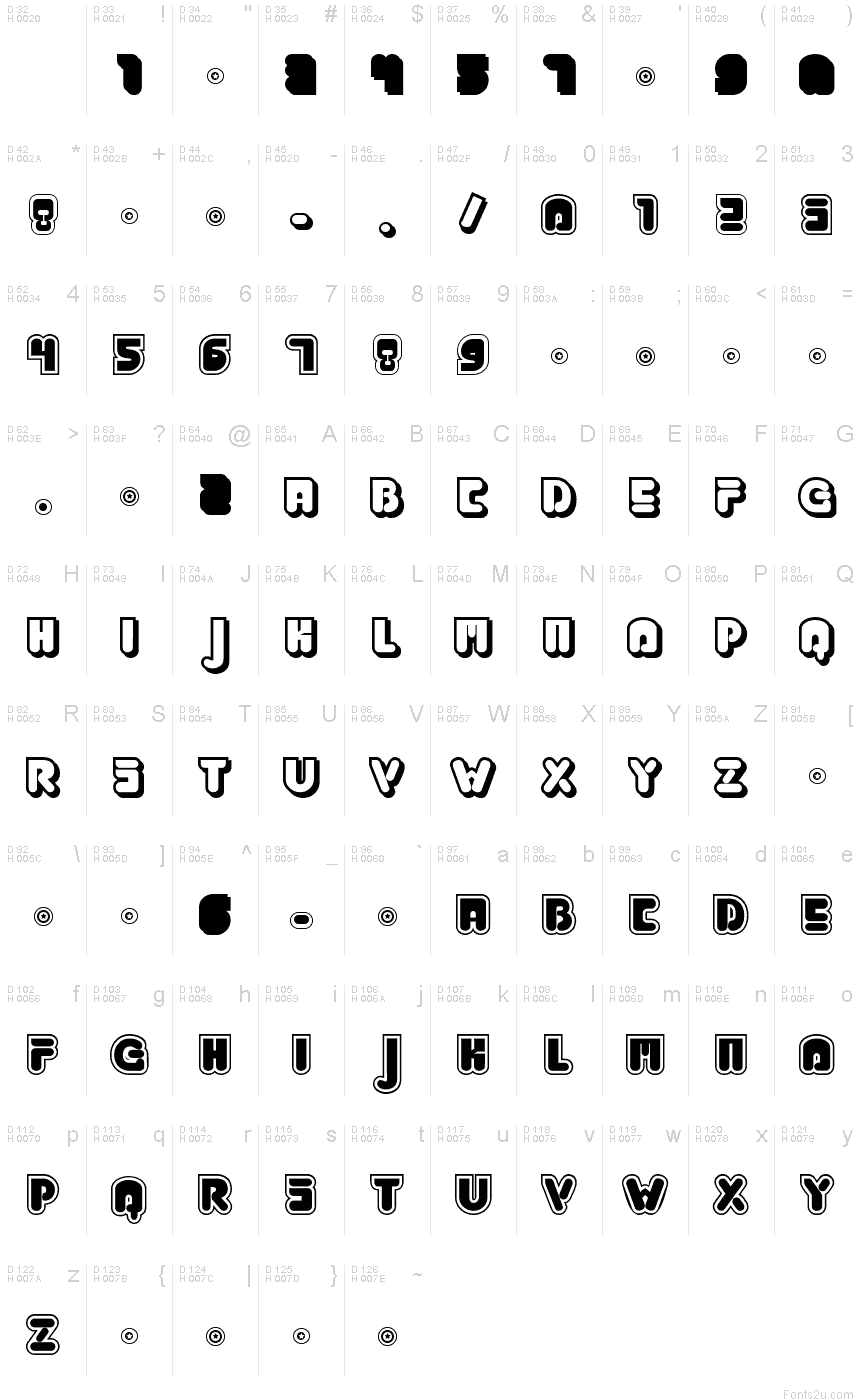
Jabbie Junior to darmowy, dekoracyjny krój displayowy o odważnym, cukierkowym charakterze. Każda litera to pękata, balonowa forma zamknięta w grubym obrysie, dzięki czemu napisy wyglądają jak naklejki na stronie. Wypełnienie liter jest gęste i wyraziste, co nadaje nagłówkom soczystą, niemal napompowaną formę, której nie da się przeoczyć.
Użyj Jabbie Junior, aby dodać energii zaproszeniom na przyjęcia dla dzieci, logo gier retro, zabawnym opakowaniom, komiksowym tytułom, plakatom i miniaturkom na YouTube. Ten darmowy font najlepiej sprawdza się w dużych rozmiarach, gdzie jego ciężkie obrysy i zaokrąglone rogi naprawdę przyciągają wzrok; w mniejszym tekście zestaw go z czystym krojem bezszeryfowym, aby zachować czytelność, podczas gdy Jabbie Junior zajmie się przyciąganiem uwagi.